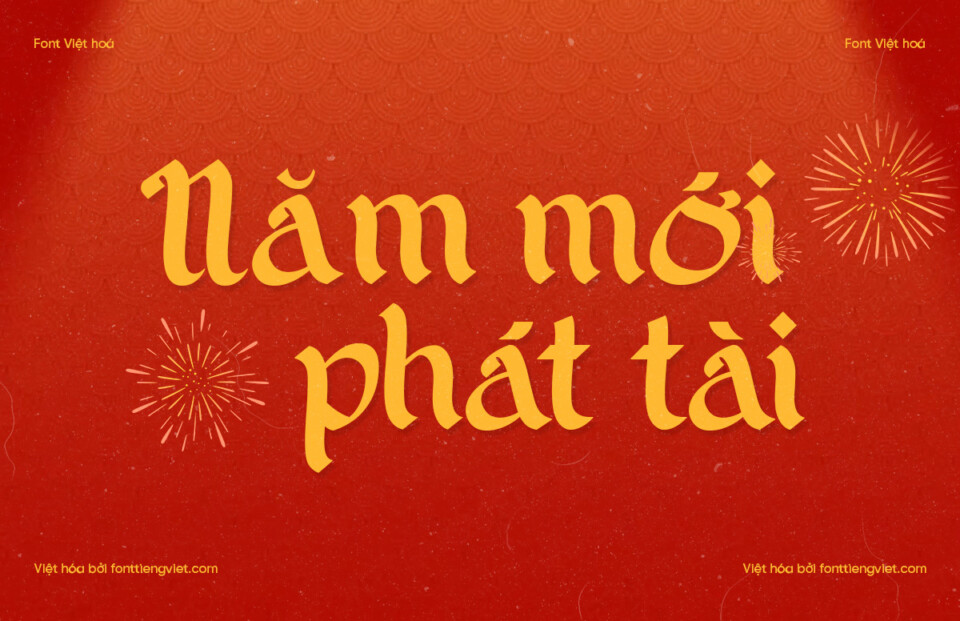
Font Việt hóa 1FTV VIP Selamat Raya – Font tết
Font Việt hóa 1FTV VIP Selamat Raya – Font tết rạng rỡ nét Xuân cho thiết kế Việt
Giới thiệu về Font Việt hóa 1FTV VIP Selamat Raya – Font tết
Trong không khí rộn ràng của những ngày giáp Tết, việc tìm kiếm một bộ Font Miễn Phí chất lượng để trang trí thiệp chúc mừng hay băng rôn sự kiện là ưu tiên hàng đầu của nhiều bạn học sinh và giáo viên. Font Việt hóa 1FTV VIP Selamat Raya – Font tết chính là lựa chọn hoàn hảo mang đến sự kết hợp tinh tế giữa nét chữ hiện đại và tinh thần truyền thống. Được đội ngũ thiết kế chăm chút kỹ lưỡng, bộ font này không chỉ hỗ trợ đầy đủ bảng mã tiếng Việt mà còn giữ trọn vẹn phong cách nghệ thuật độc đáo của bản gốc, giúp các tác phẩm đồ họa trở nên sống động và bắt mắt hơn bao giờ hết trong dịp đầu năm mới.
Đặc điểm nổi bật của Font Việt hóa 1FTV VIP Selamat Raya – Font tết
Phong cách thiết kế mang đậm hơi thở lễ hội
Đặc trưng lớn nhất của Font Việt hóa 1FTV VIP Selamat Raya – Font tết nằm ở các đường nét uốn lượn mềm mại nhưng vẫn giữ được sự chắc chắn và rõ ràng. Các nét chữ được cách điệu một cách khéo léo, gợi nhắc đến hình ảnh những dải lụa đỏ hay những cánh hoa xuân đang đua nở. Điều này giúp bộ font cực kỳ phù hợp cho các tiêu đề lớn, các câu chúc Tết ý nghĩa hay những khẩu hiệu chào mừng năm mới tại trường học. Sự mềm mại của font chữ tạo ra cảm giác ấm áp, gần gũi, giúp người xem cảm nhận được sự chân thành và niềm vui trong mỗi thông điệp mà bạn muốn truyền tải.
Tối ưu hóa khả năng hiển thị và gõ tiếng Việt
Một vấn đề thường gặp khi sử dụng các font ngoại nhập là lỗi font khi gõ tiếng Việt có dấu. Tuy nhiên, với phiên bản Font Việt hóa 1FTV VIP Selamat Raya – Font tết, mọi rào cản về ngôn ngữ đã được loại bỏ hoàn toàn. Các dấu thanh như huyền, sắc, hỏi, ngã, nặng được đặt ở vị trí chuẩn xác, cân đối với thân chữ, đảm bảo tính thẩm mỹ cao nhất. Bên cạnh đó, font chữ này có độ tương phản tốt, giúp văn bản dễ đọc ngay cả khi in ấn trên khổ lớn hay hiển thị trên màn hình điện thoại, máy tính. Đây là một điểm cộng lớn cho các bạn học sinh khi làm báo tường điện tử hoặc thiết kế ảnh bìa Facebook mừng Xuân.
Ứng dụng thực tế của Font Việt hóa 1FTV VIP Selamat Raya – Font tết
Sáng tạo thiệp chúc mừng và quà tặng ý nghĩa
Sử dụng Font Việt hóa 1FTV VIP Selamat Raya – Font tết để thiết kế thiệp chúc mừng là một cách tuyệt vời để thể hiện sự sáng tạo cá nhân. Bạn có thể dùng font này cho các cụm từ như “Chúc Mừng Năm Mới”, “An Khang Thịnh Vượng” hay “Vạn Sự Như Ý” để tạo điểm nhấn thị giác mạnh mẽ. Kết hợp với các tông màu đỏ, vàng đặc trưng của ngày Tết, bộ font sẽ giúp tấm thiệp của bạn trở nên chuyên nghiệp và đầy tính nghệ thuật. Đối với các thầy cô giáo, việc sử dụng font chữ này trong các bài giảng điện tử dịp cuối năm cũng góp phần tạo thêm hứng khởi và niềm vui cho các em học sinh trong những tiết học ngoại khóa về văn hóa truyền thống.
Trang trí không gian lớp học và sự kiện trường học
Ngoài các sản phẩm in ấn nhỏ, font chữ này còn phát huy tác dụng tối đa trong việc thiết kế backdrop sân khấu cho các buổi văn nghệ chào Xuân. Với kích thước chữ lớn, các đường nét của Font Việt hóa 1FTV VIP Selamat Raya – Font tết vẫn giữ được độ sắc nét, không bị nhòe hay vỡ nét. Các bạn có thể ứng dụng để làm banner, poster thông báo các cuộc thi gói bánh chưng, hội hoa xuân tại trường. Sự đồng bộ trong phông chữ thiết kế sẽ giúp không gian lễ hội trở nên chỉn chu và trang trọng hơn, mang lại những kỷ niệm đẹp cho tập thể lớp và nhà trường.
Kết luận về bộ Font Việt hóa 1FTV VIP Selamat Raya – Font tết
Có thể khẳng định rằng, việc sở hữu một bộ font chữ đẹp và chuẩn Việt hóa sẽ giúp công việc thiết kế của bạn trở nên nhẹ nhàng và hiệu quả hơn rất nhiều. Với những ưu điểm vượt trội về thẩm mỹ và tính ứng dụng, Font Việt hóa 1FTV VIP Selamat Raya – Font tết xứng đáng có mặt trong bộ sưu tập tài nguyên đồ họa của bất kỳ ai yêu thích cái đẹp. Đừng ngần ngại trải nghiệm ngay bộ font tuyệt vời này để làm mới các dự án sáng tạo của mình. Để cập nhật thêm nhiều bộ font ấn tượng khác cho học tập và công việc, bạn hãy thường xuyên truy cập Font Miễn Phí, Font Việt Hóa, Font Việt hóa 1FTV VIP Selamat Raya – Font tết để nhận được những tài liệu chất lượng nhất hoàn toàn miễn phí nhé.